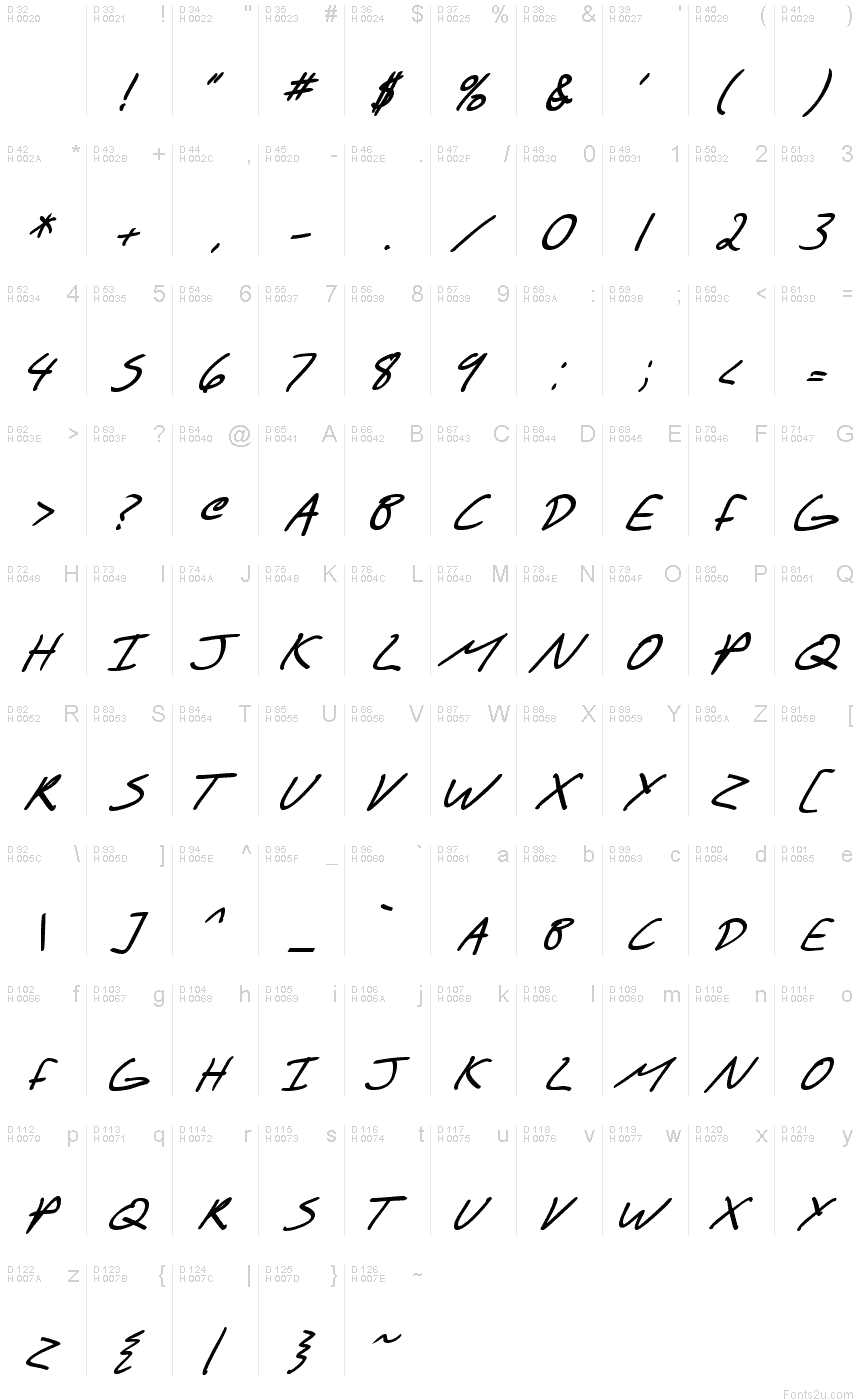
SF Scribbled Sans SC Bold Italic od ShyFoundry to bezpłatny krój pisma z dużymi literami, który oddaje energię i charakter szybkiego pisma pisakiem. Litery nachylają się do przodu w długich, pętelkowych pociągnięciach, z szerokimi łukami i nagłymi, ostrymi zwrotami, dzięki czemu alfabet wydaje się improwizowany, niespokojny i nieco nieujarzmiony.
Świetnie sprawdza się na plakatach, grafikach skate i streetwear, okładkach mixtape'ów czy zinów, tytułach i dużych inicjałach, wszędzie tam, gdzie font ma być szybki, a nie idealnie wygładzony. Ponieważ litery rozciągają się i przecinają w swobodnym, odręcznym rytmie, sprawdza się również w krótkich hasłach brandingowych, monogramach i tekstach na okładki, które mają wyglądać, jakby powstały jednym, pewnym ruchem.
SF Scribbled Sans SC
SF Scribbled Sans SC Bold Italic
ShyFoundry
Derek Vogelpohl